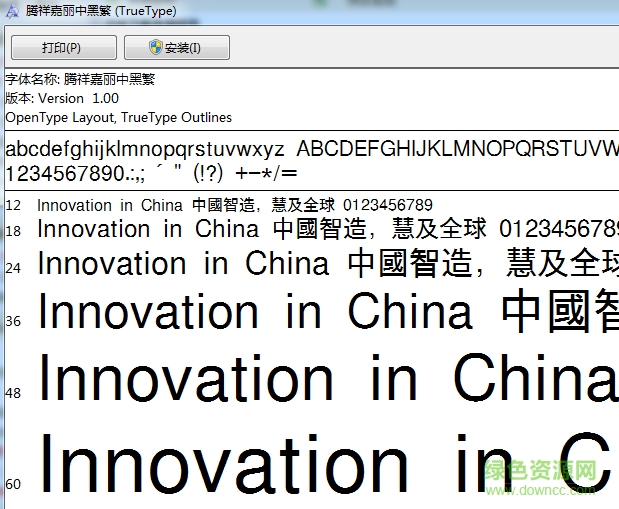
騰祥嘉麗中黑繁字體是騰祥嘉麗字體中的一款繁體字體,字型非常正式大氣,給用戶一種踏實(shí)感。有喜歡的朋友可以來(lái)綠色資源網(wǎng)免費(fèi)下載使用!
騰祥嘉麗中黑繁字體是中文字體庫(kù)中的一款繁體字體,該字體十分具有個(gè)性,如果您需要的話,就趕快來(lái)綠色資源網(wǎng)下載吧!